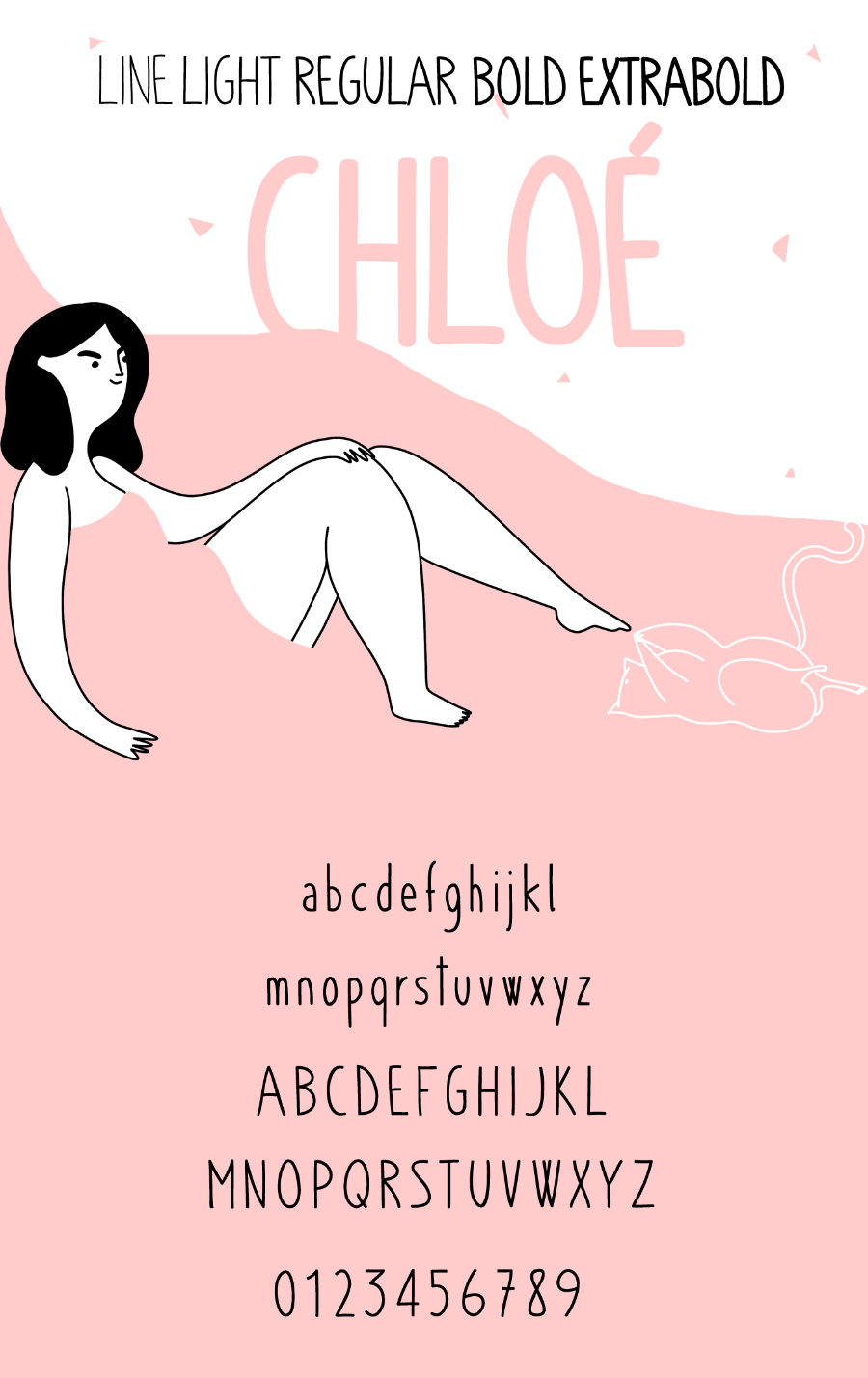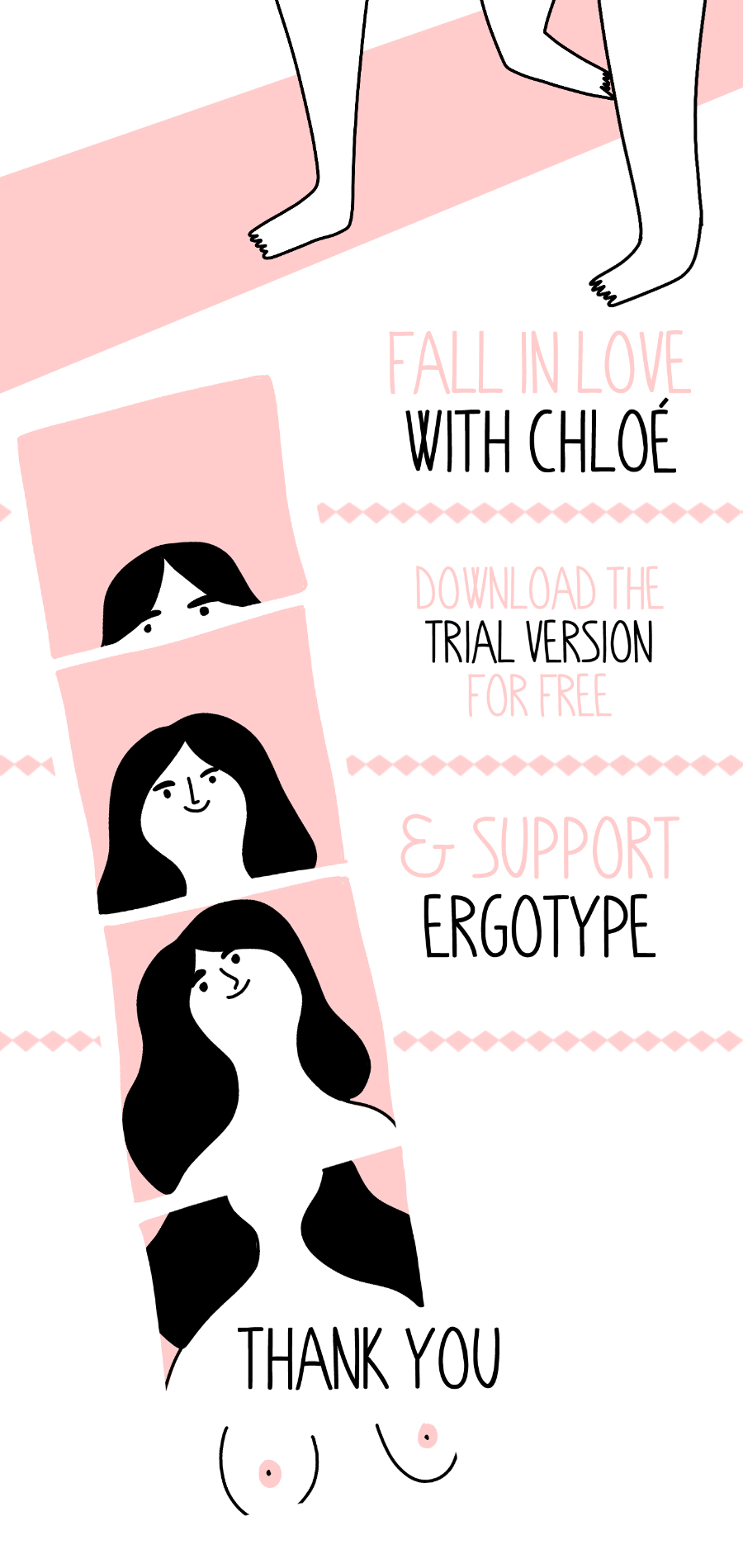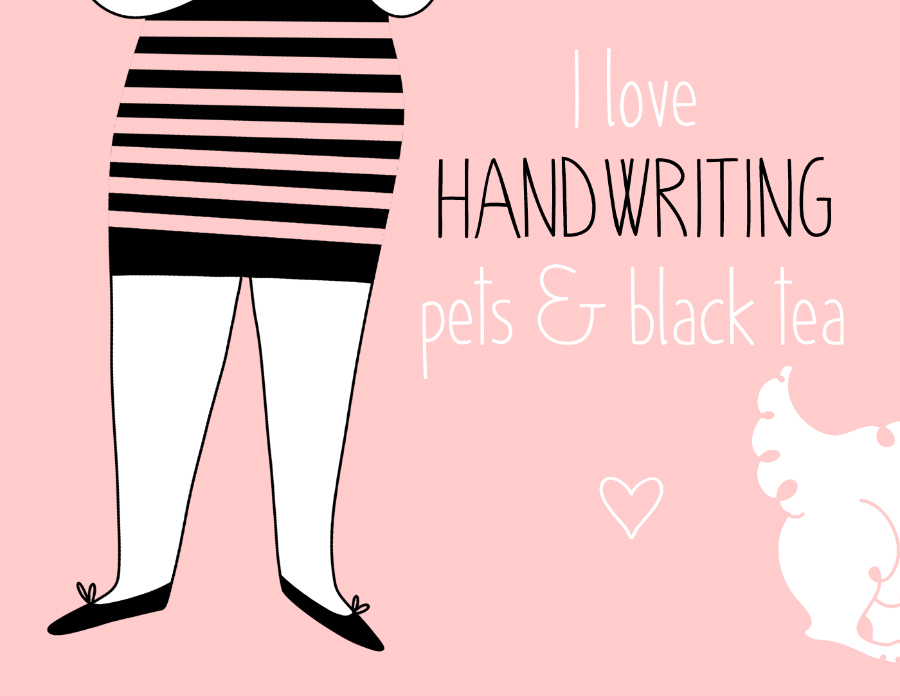
Chloé手写免费字体
Chloé Handwriting Free Font
Chloé手写免费字体是一个惊人的手写无衬线字体。这个字体来自GUD又名Giulia Ursenna Dorati Ergotype,在Ergonauth制作的数字字体代工厂。 Chloé是女性化的,简直是令人惊艳的,它为许多设计目的很好。因此,它在包装,印刷设计,标志和品牌方面也会看起来不错。